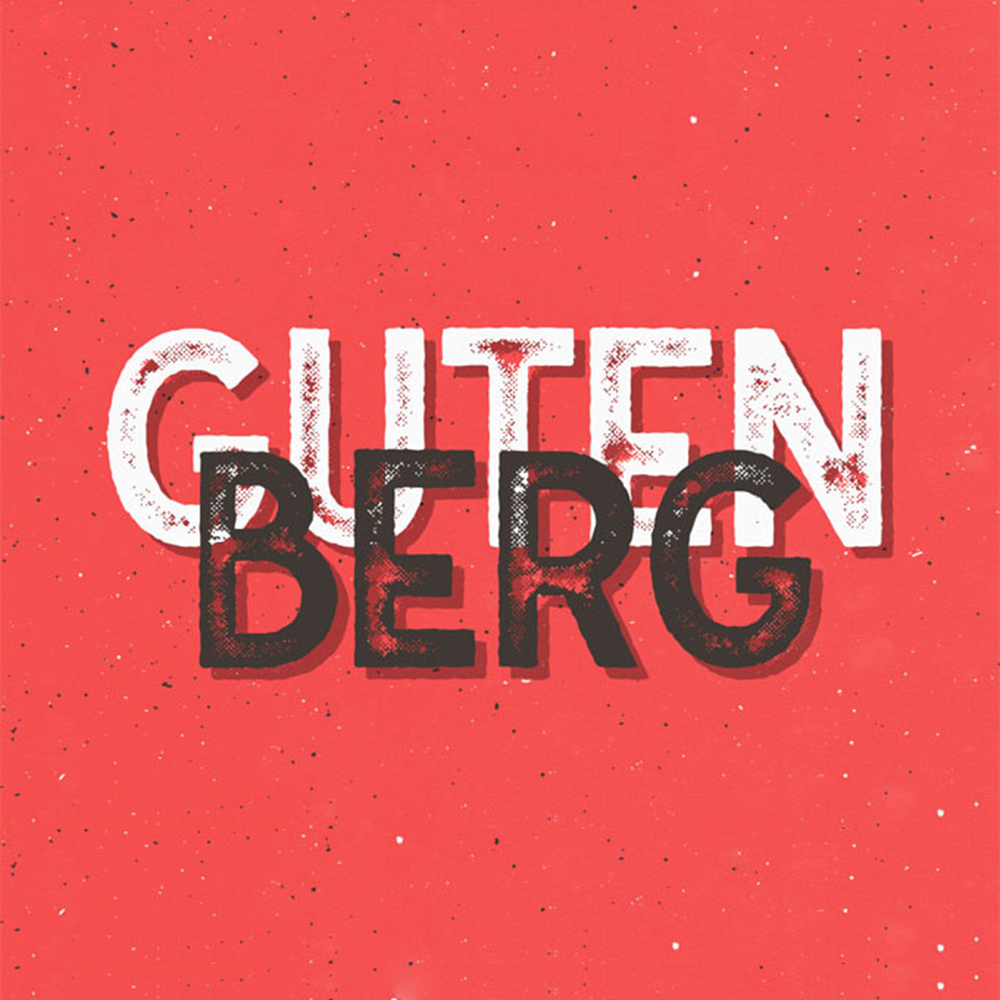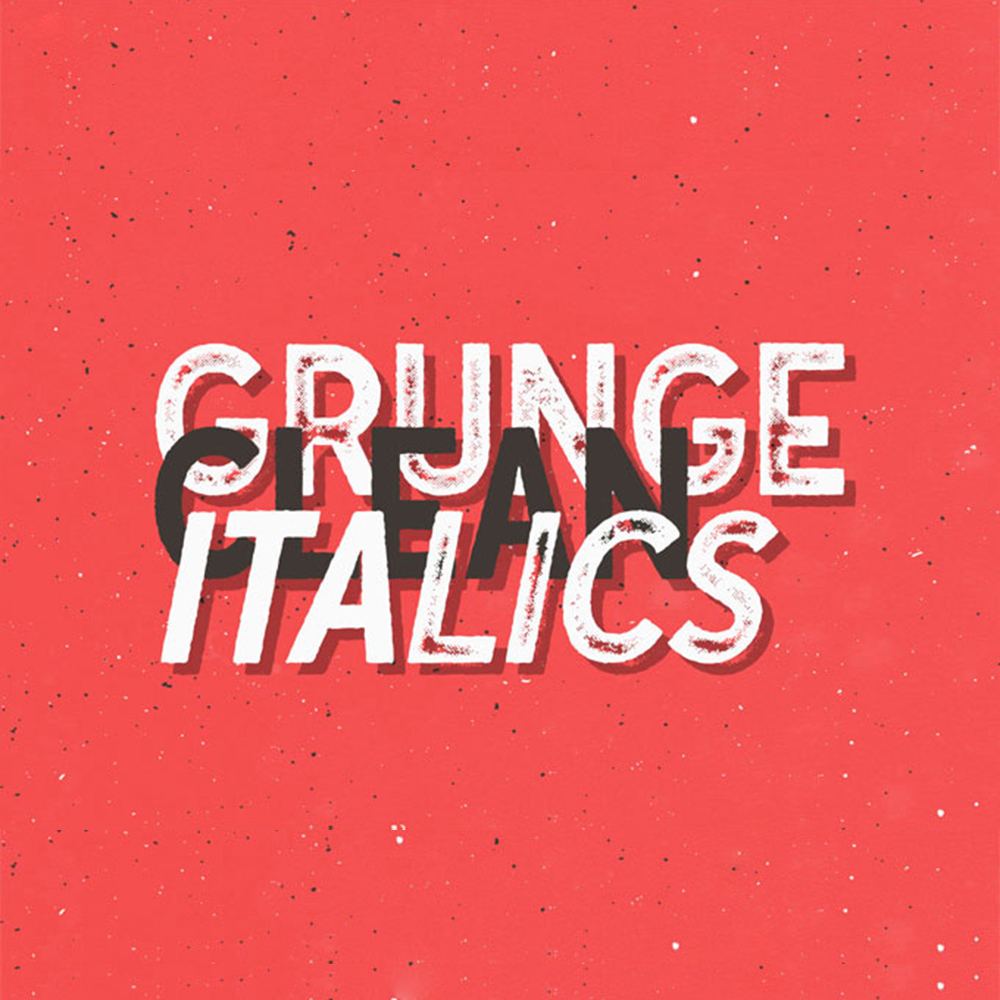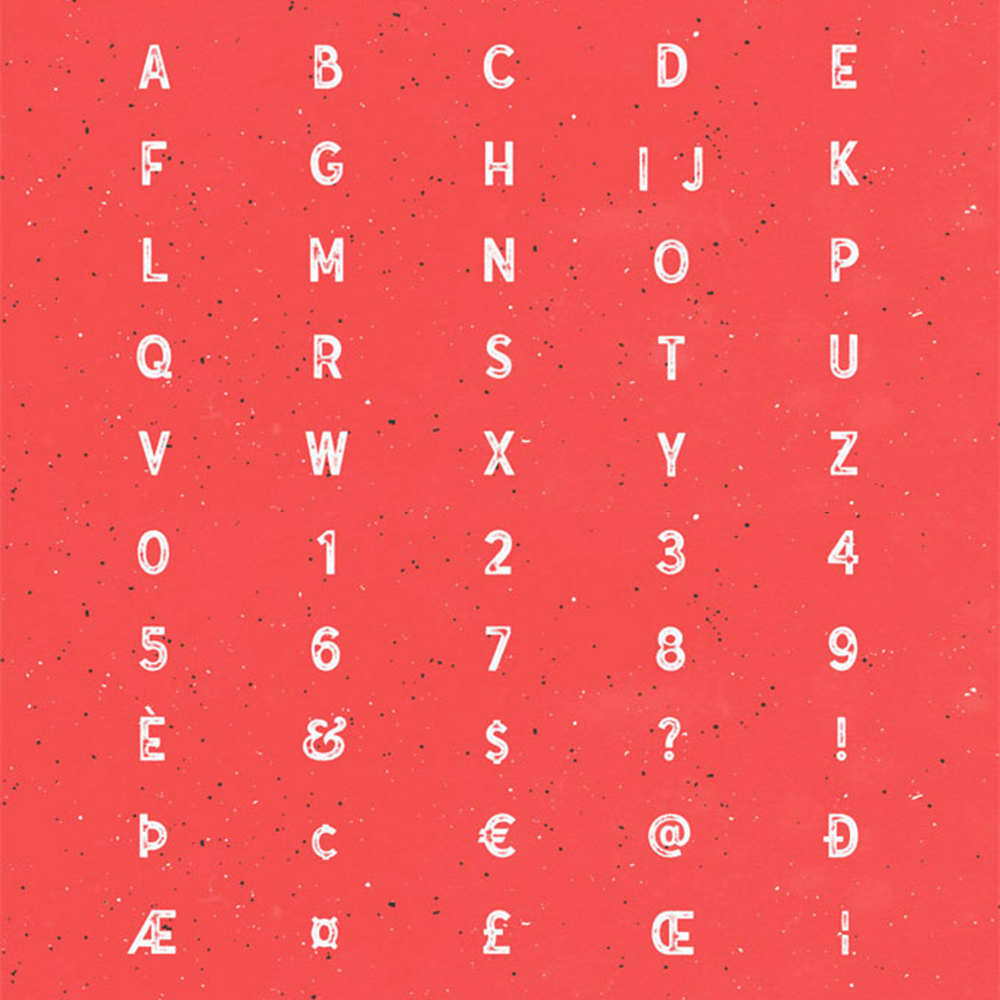
فونت پرمیوم و انگلیسی Gutenberg Font با ارائه اشکال نامنظم که انتقال جوهر را تقلید میکنند، به یوهانس گوتنبرگ ادای احترام میکند. این خانواده فونت که برای…
فونت پرمیوم و انگلیسی Gutenberg Font با ارائه اشکال نامنظم که انتقال جوهر را تقلید میکنند، به یوهانس گوتنبرگ ادای احترام میکند. این خانواده فونت که برای افزودن حس و حال قدیمی عالی است، به کار شما ظاهری اصیل میبخشد! این فونت دارای چهار استایل و لبههای جوهری طرحدار، ۲۹۶ علامت و پشتیبانی از چند زبان است. شما میتوانید بسته به اهداف و جلوه دلخواه خود، بین یک سبک خشن و تمیز انتخاب کنید. نقصهای عمدی جوهری این فونت مطمئناً هر نوع نیاز طراحی مانند لوگو، تبلیغات، ایدههای برندسازی، تبلیغات تجاری، چاپ، پروژههای طراحی وب و ارائهها را برآورده میکند.